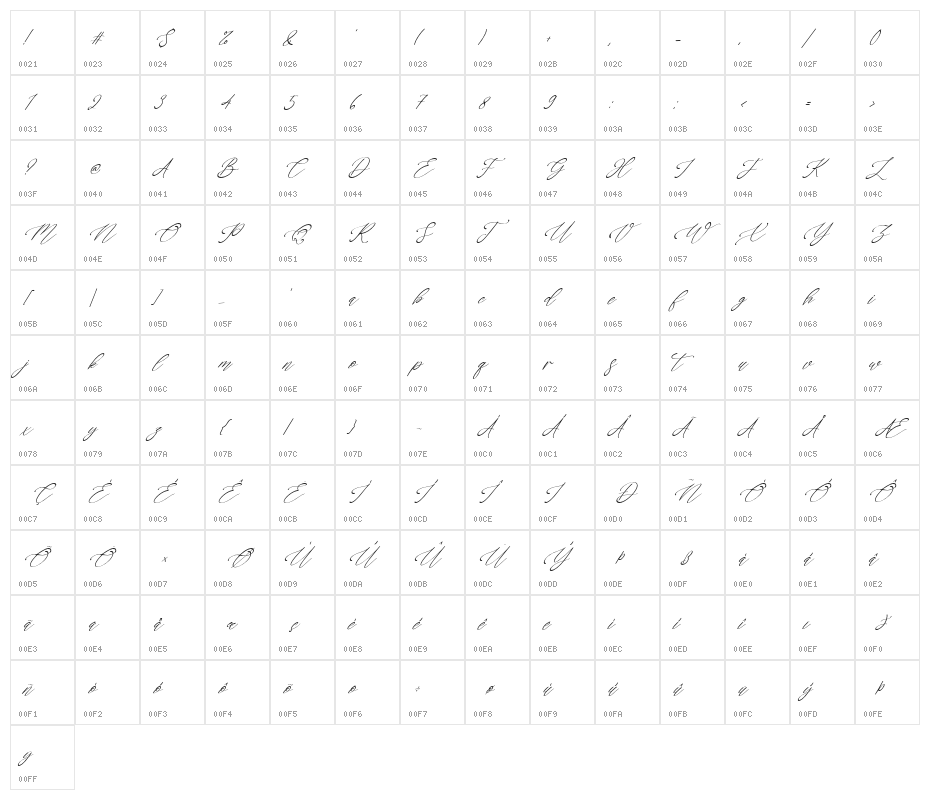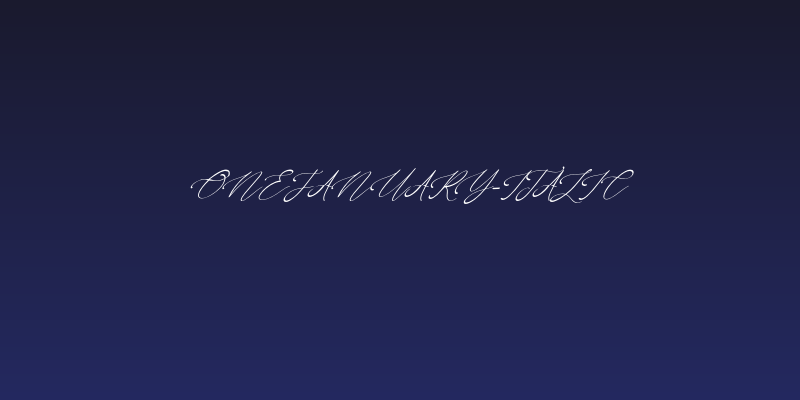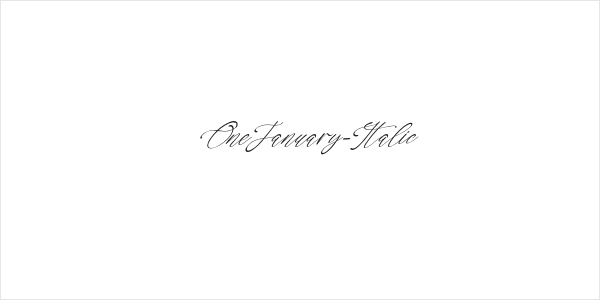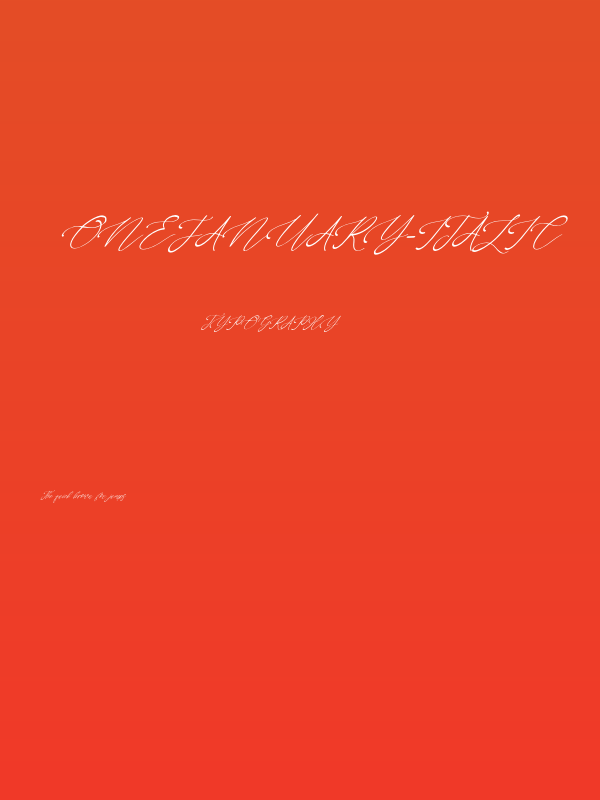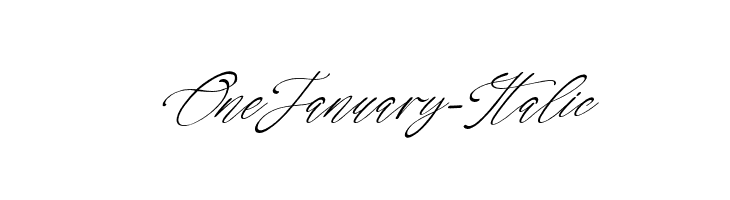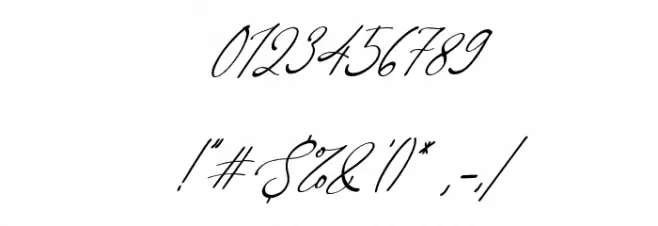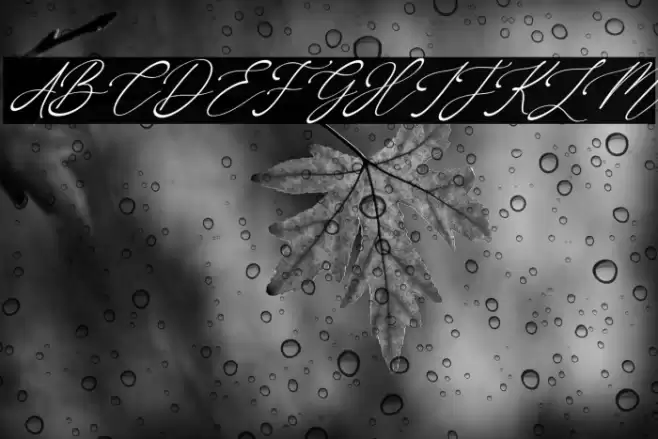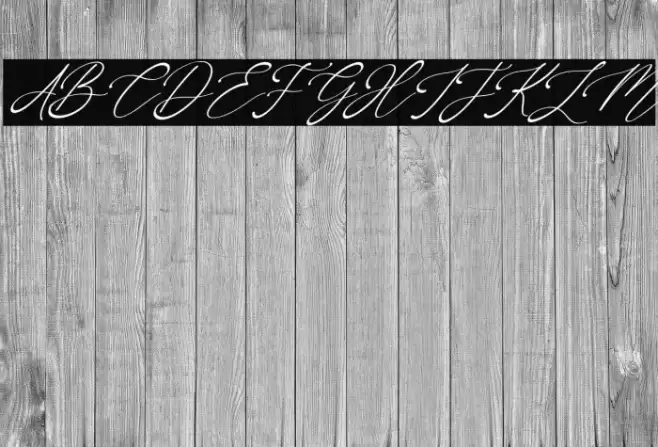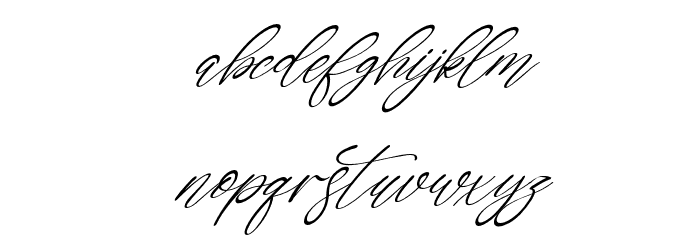
OneJanuary-Italic Font
✎ Script
| Kategorien | Script |
| Gesamtstil | Elegant |
| Anwendungsfall | Logos, Invitations, Branding |
| Vorgeschlagene Projekte | Ideal for wedding invitations, elegant branding, luxury product packaging, and formal event materials. |
OneJanuary-Italic
| Kategorien | Script |